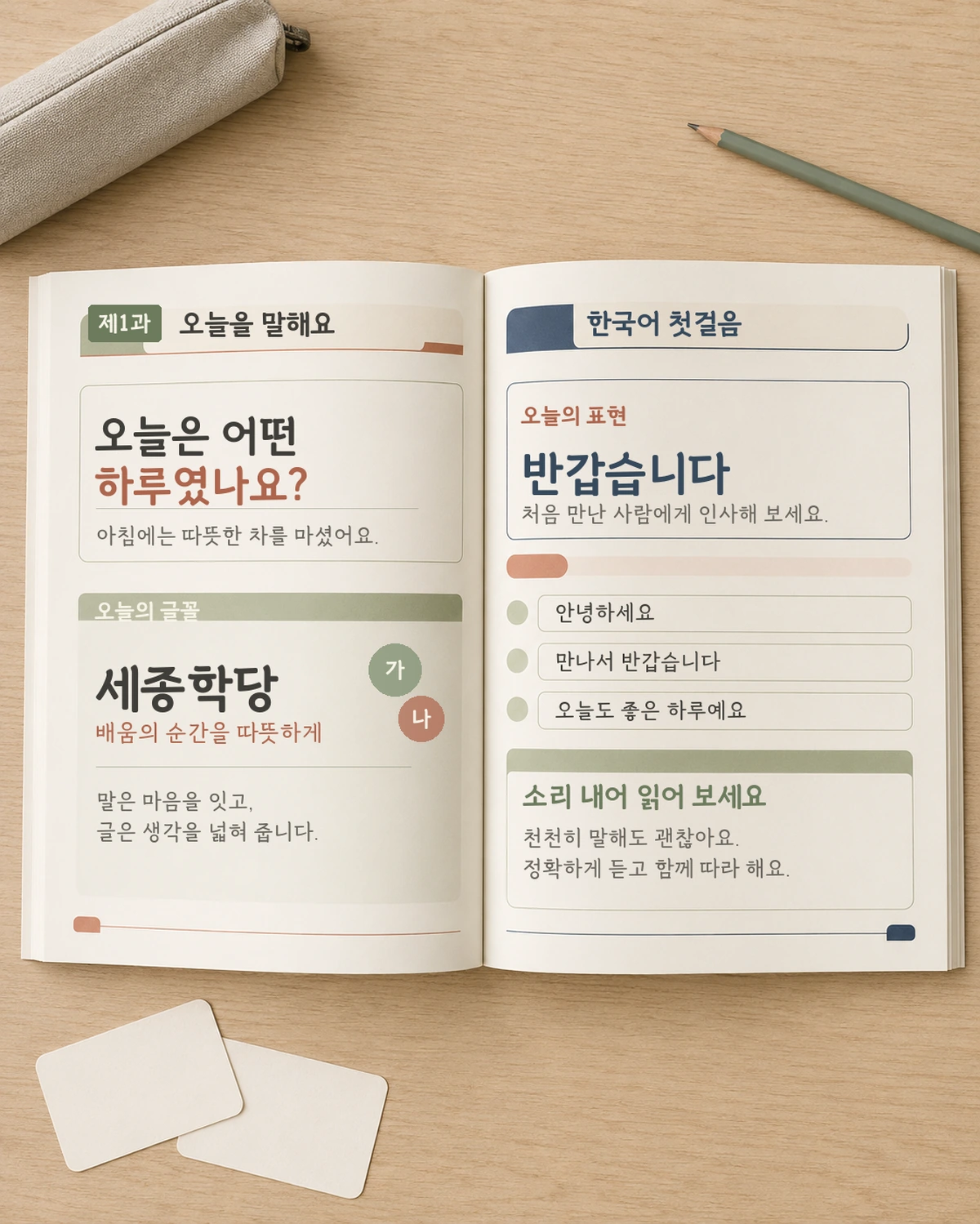
세종학당 무료폰트
세종학당 — 세종학당재단에서 배포하는 무료 폰트입니다. 바탕체의 안정적인 구조에 부드러운 곡선과 손글씨의 온기를 담은 교육용 서체
세종학당재단이 창립 10주년을 맞아 한컴그룹, 윤디자인그룹과 함께 만들어 2022년 10월에 공개한 서체입니다. 세종학당은 외국인에게 한국어와 한국문화를 가르치는 기관이라, 만드는 목적도 거기에 맞춰졌습니다.
모티브가 한글 쓰기의 뼈대인 바탕체입니다. 외국인 학습자가 손으로 따라 쓰기 쉽도록 하는 것이 출발점이었습니다. 제작사가 밝힌 조형은 이렇습니다. 자음 ㅇ은 바탕체의 특징을 살려 정원의 형태를 최대한 유지했고, 둥근 획과 꺾임의 형태를 굴림으로 처리해 손글씨 같은 따뜻한 느낌을 냈다는 것입니다. 재단은 제목체의 시각 중심선을 위쪽에, 본문체는 위쪽에서 가운데에 두어 각각 주목성과 가독성을 확보했다고 덧붙입니다.